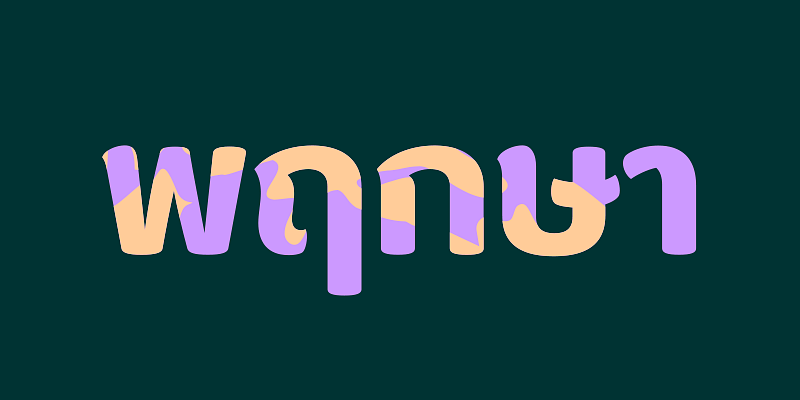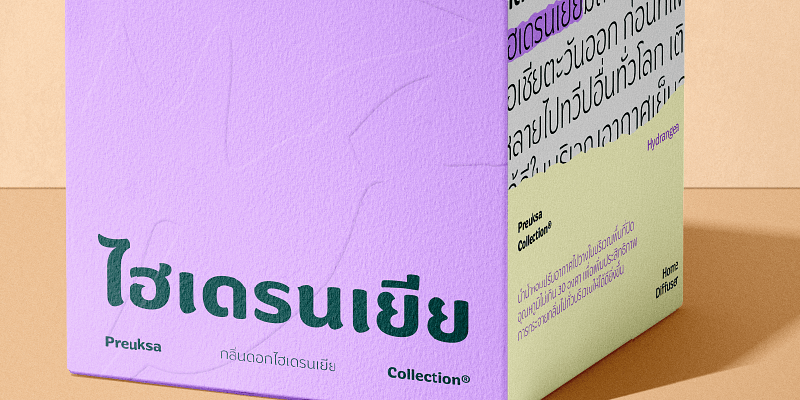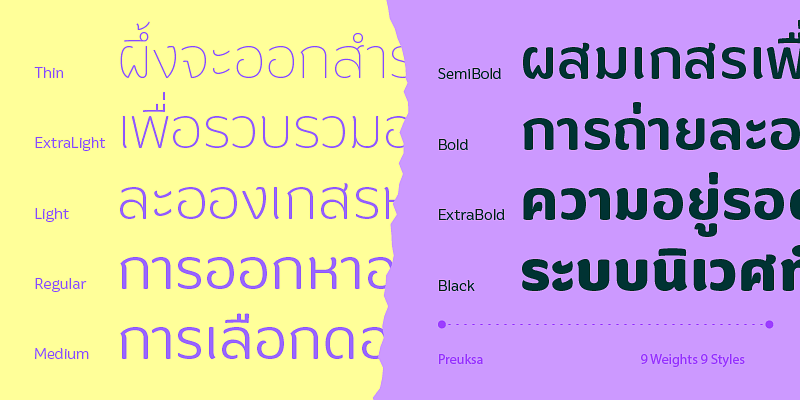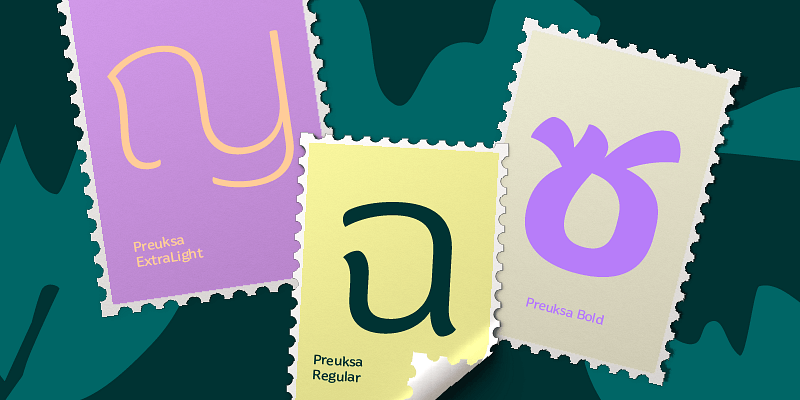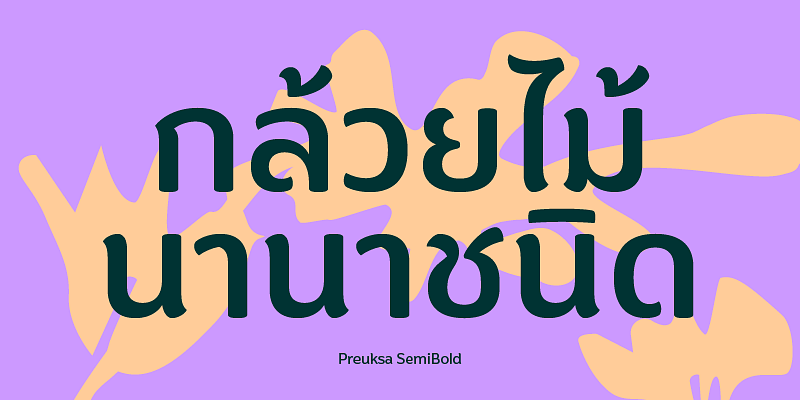
Der lateinische Zeichensatz von Prueksa ist eine Organic Sans Serif, die ein Gegengewicht zu Industrial Sans Serif bildet und für Abwechslung in der Sammlung lateinischer Schriften von Cadson Demak sorgen soll. Darüber hinaus wurde ein thailändischer Schriftsatz ohne Schleifen hinzugefügt, der ursprünglich „Amino“ hieß, bevor er 2022 entwickelt und in Preuksa umbenannt wurde. Er verfügt über alternative Zeichen für verschiedene Anwendungen und stellt Benutzern eine Schriftfamilie mit 9 Strichstärken und 9 Stilen zur Auswahl.